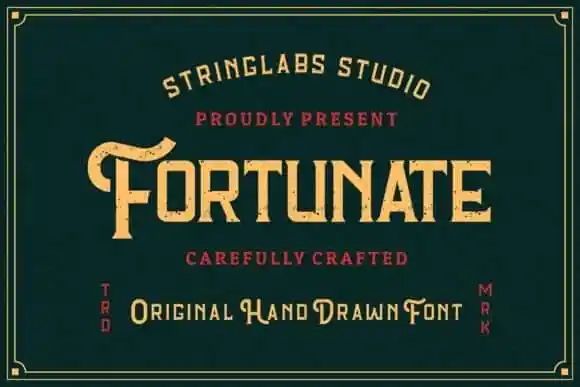
A Fortunate Display Font oferece uma aparência marcante e natural, perfeita para projetos futuros. Esta tipografia foi criada por StringLabs e apresentada pelo 99designs. Com um visual forte, a Fortunate é sofisticada e destaca-se por seus caracteres grosso e prolongados. Ela se destacará especialmente em logos, identidade de marca, embalagens e projetos visuais diversos. É uma fonte de exibição mestre que merece ser sua escolha definitiva para qualquer aplicação visual onde desejará criar um impacto imediato. Experimente a Fortunate Display Font para adicionar originalidade e elegância ao seu próximo projeto.